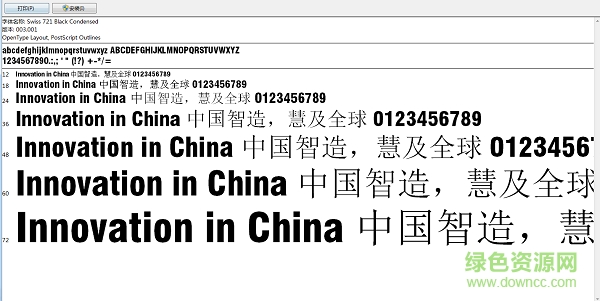
swiss721bt black
swiss721bt字體全套收錄了swiss721bt black、swiss721bt roman、swiss721bt bold、swiss721bt heavy、swiss721bt light等全套字體,辨認(rèn)效果良好,需要的朋友快來下載吧!
swiss721bt blackextended